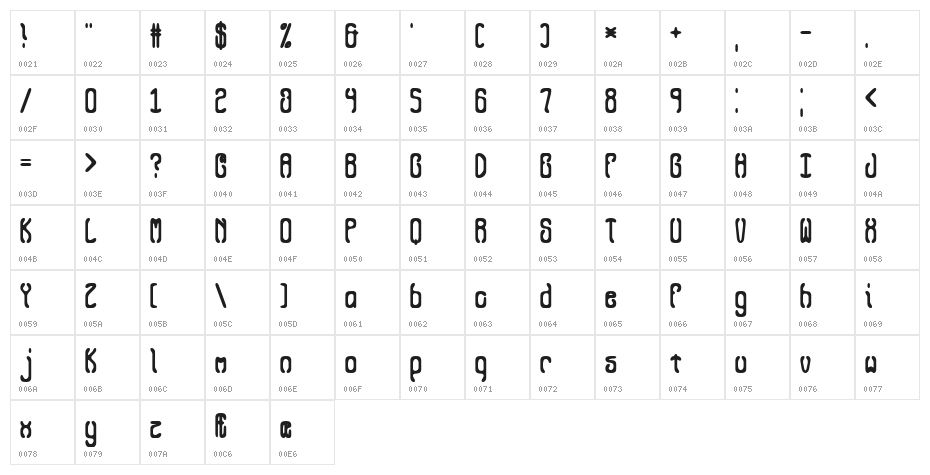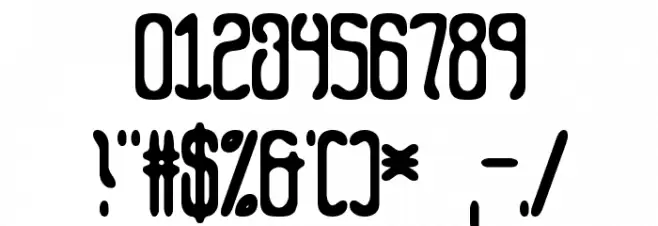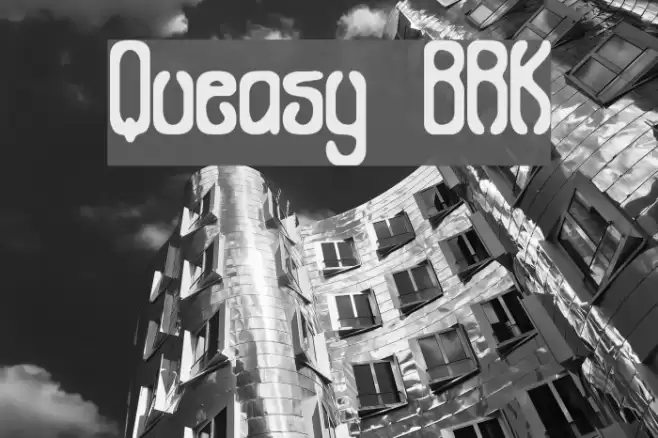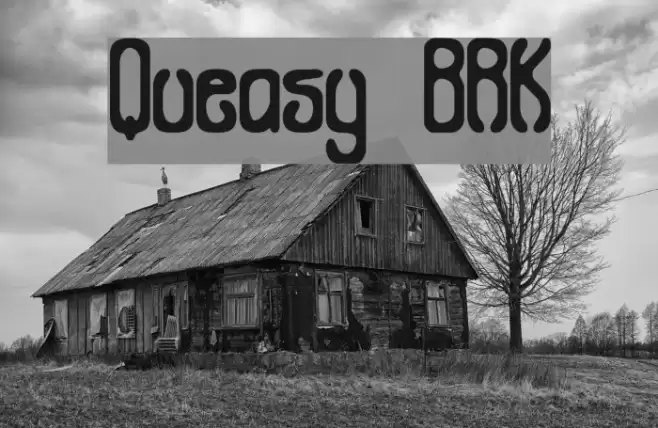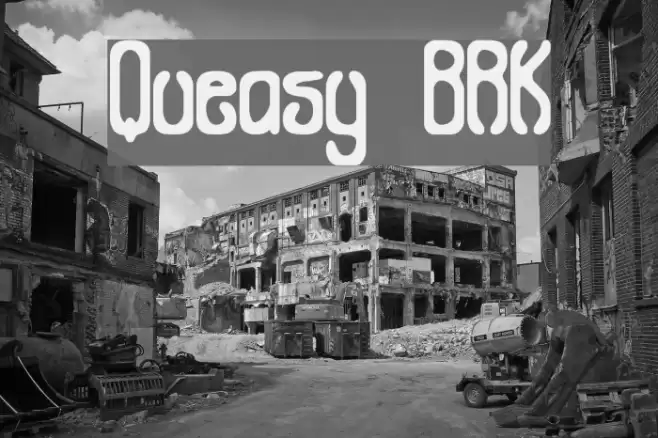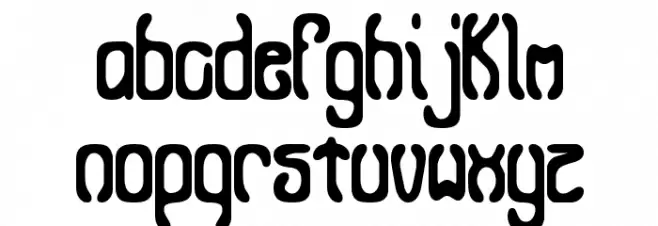
Queasy BRK Font
| Stile generale | Playful, Modern |
| Progetti proposti | Ideal for children's books, playful branding, posters, and creative digital content. |